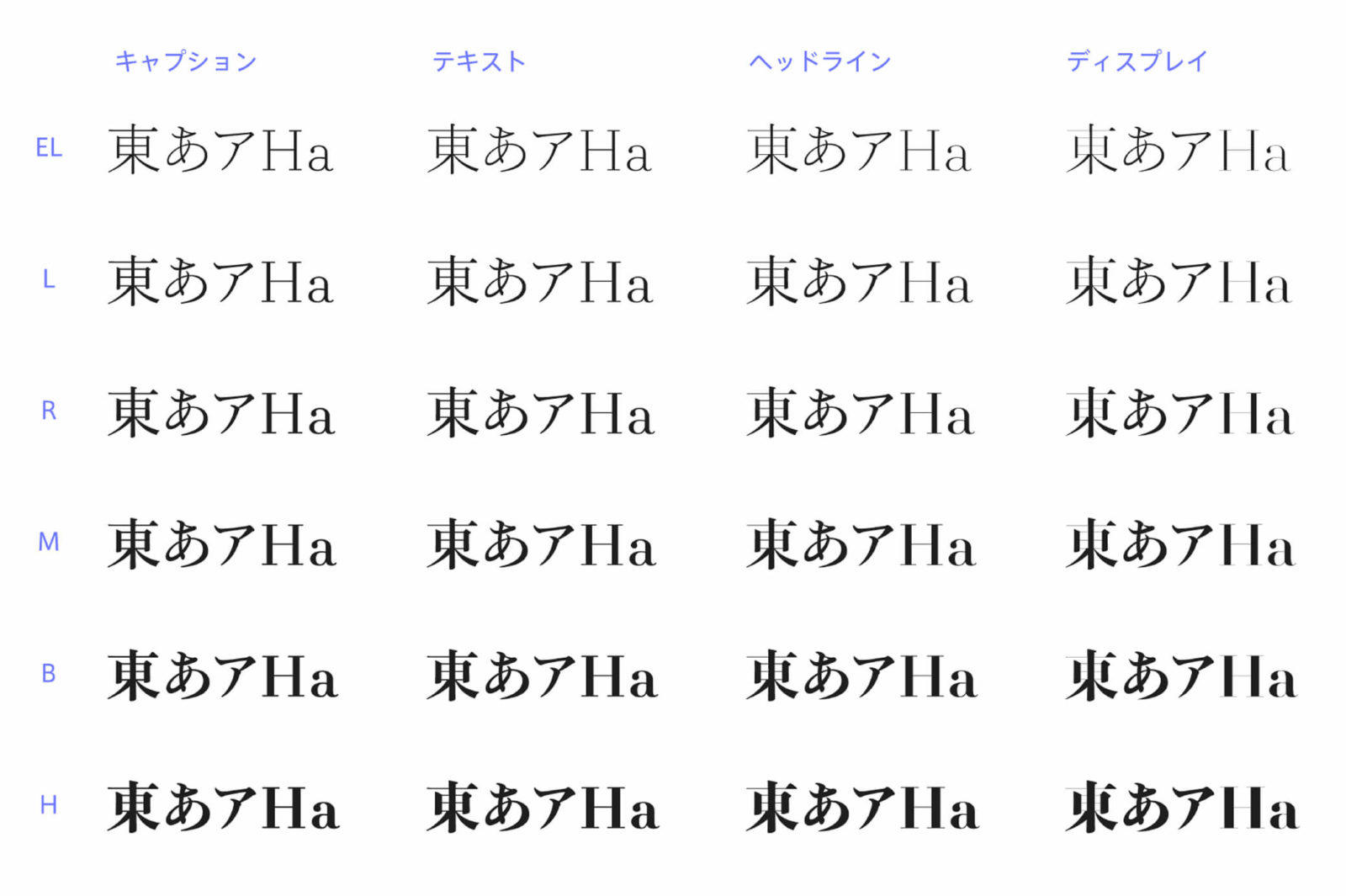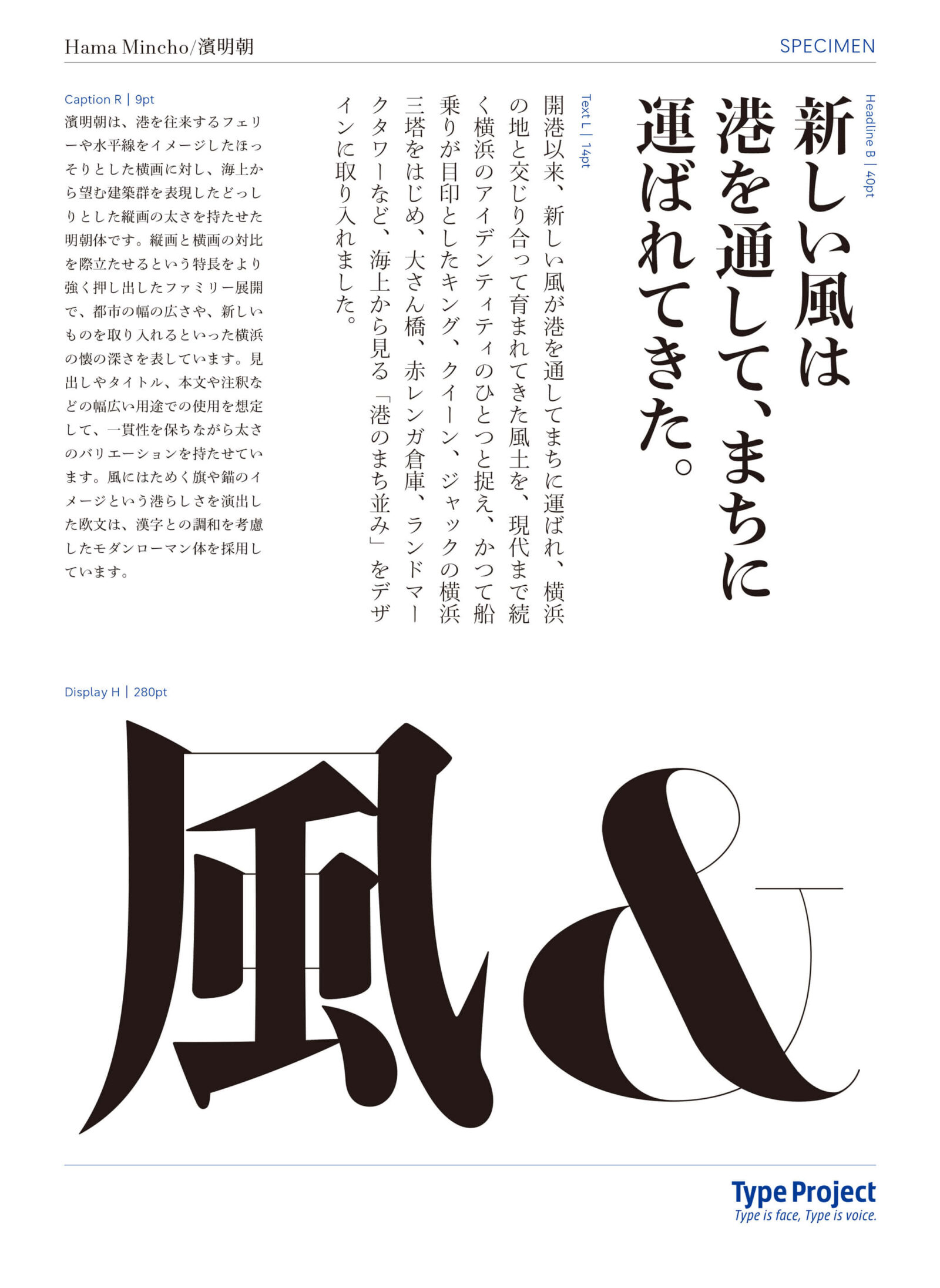
横浜のスケールや特徴を取り入れ、縦画と横画の対比を際立たせた明朝体
タイププロジェクト株式会社(東京都練馬区 代表取締役社長 鈴木 功、以下タイププロジェクト)は本日、都市フォントプロジェクトのひとつとして、横浜をイメージして開発した「濱明朝」の発売を開始したことを発表しました。濱明朝は、港を往来するフェリーや水平線をイメージしたほっそりとした横画に対し、海上から望む建築群を表現したどっしりとした縦画の太さを持たせた明朝体です。縦画と横画の対比を際立たせるという特長をより強く押し出したファミリー展開で、都市の幅の広さや、新しいものを取り入れるといった横浜の懐の深さを表しています。
濱明朝は、見出しやタイトル、本文や注釈などの幅広い用途での使用を想定して、一貫性を保ちながら太さのバリエーションを持たせています。キャプション、テキスト、ヘッドライン、ディスプレイの4つのバリエーションで、それぞれ6ウエイトの計24フォントのファミリーです。
濱明朝
濱明朝は、大佛次郎記念館のサインや、天野和俊デザイン事務所が最優秀賞を受賞した横浜市中区馬車道商店街協同組合の150年記念ロゴタイプに採用されるなど、横浜での採用が広がっています。
ウエイト: EL (エクストラライト)、L (ライト)、R (レギュラー)、M (ミディアム)、B (ボールド)、H (ヘヴィ)